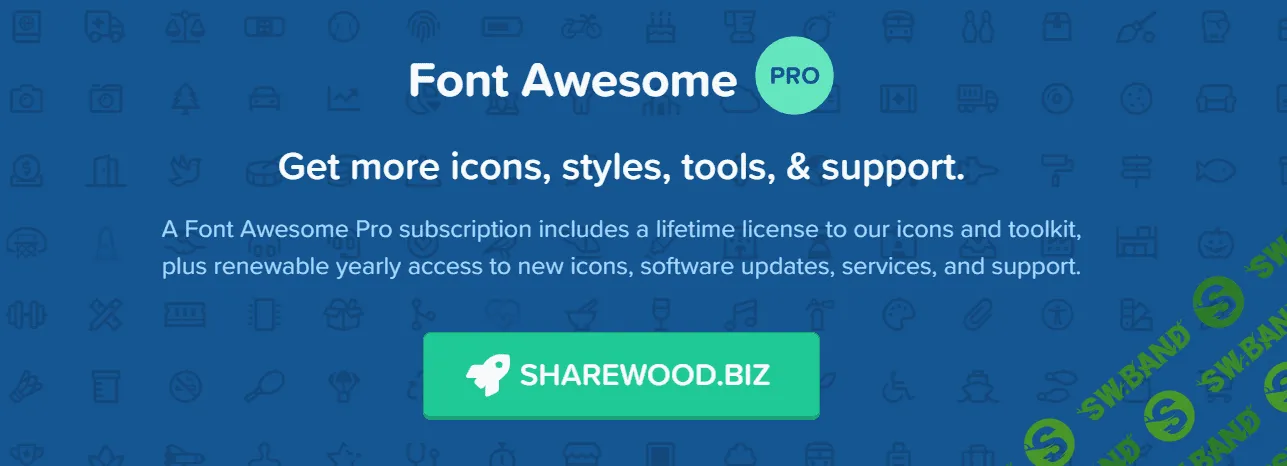
Название: Font Awesome Pro v5.7.0
Описание:
Font Awesome Pro - новая версия иконочного шрифта и CSS-инструментария. Font Awesome PRO предлагает вам масштабируемые векторные иконки, которые вы можете с легкостью персонализировать - размер, цвет, тени и все, что можно сделать силами CSS. В новой 5.4.1 версии были добавлены 379 иконок.
5.7.0 - 2019-01-28
Added
New Food category
More Medical icons
More icons from the leaderboard
Added tasks-alt
New CSS class fa-flip-both that applies fa-flip-horizontal and fa-flip-vertical together
CSS now defaults to font-display: auto
Sass and Less files contain a variable that can be changed to alter the font-display value
Changed
Updated slack brand icon
Reverted calendar-alt to previous design before 5.6.0
Fixed
Safari fails to process pseudo elements if the font-weight is "normal"
Corrected font weights in TTF files FortAwesome/Font-Awesome#13320
XCode now correctly displays different styles when using TTF files